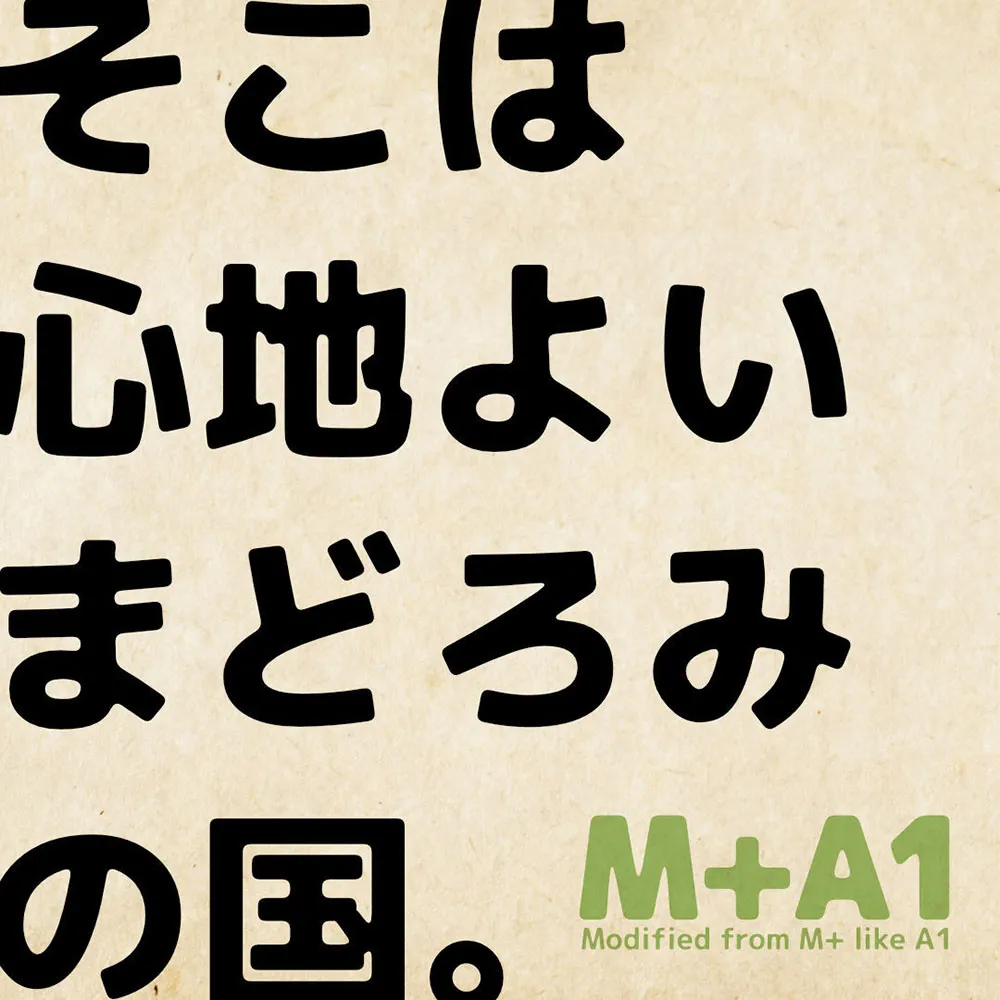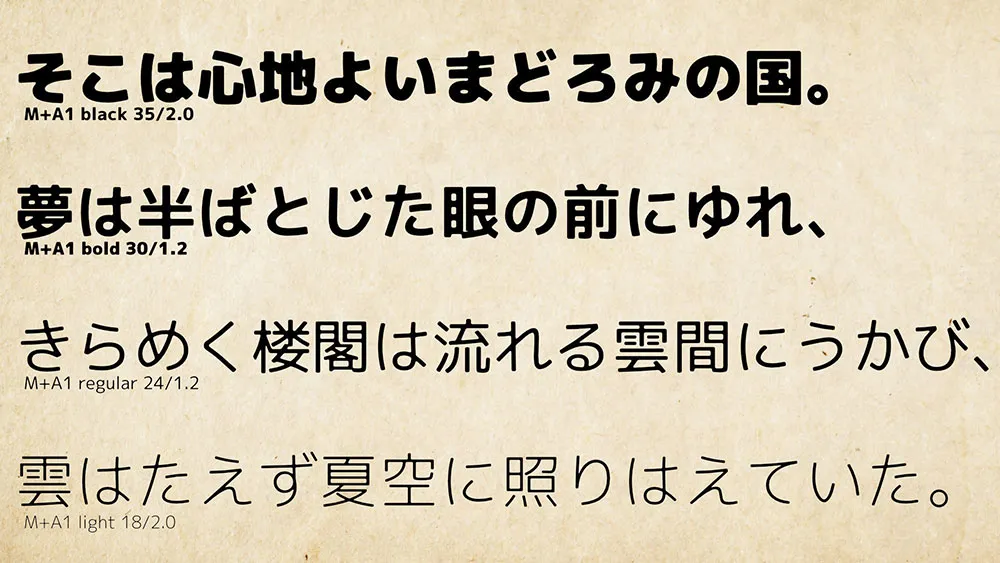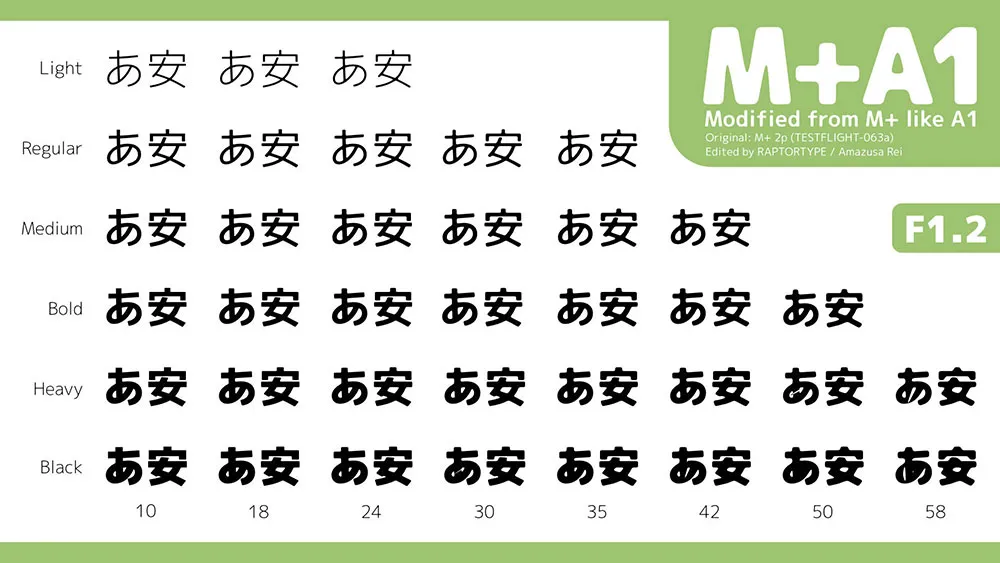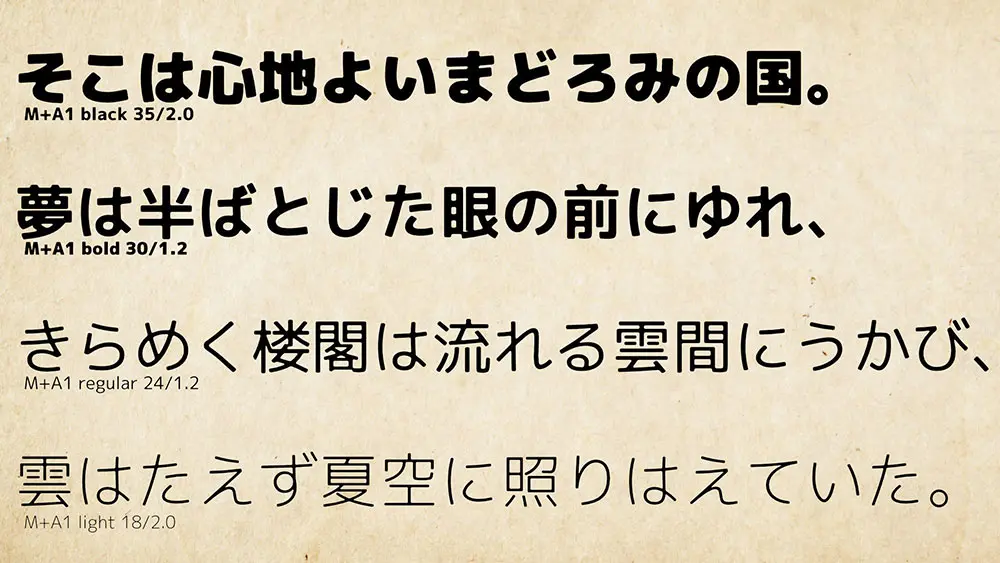
M+A1預覽
M+A1介紹
M+A1字體是對M+ FONTS進行修改,利用Python機械地進行了圓角、油墨彙集處理的字體。每個字體包含 8000 多個字符,共有74個版本。可商用,可重新發布、修改。由於機械性地編輯,一部分的文字崩塌了,使用的時候請注意。
「M+A1」フォントはM+ FONTSを改変し、Pythonにより機械的に角丸・墨溜まり処理を施した書體です。1フォント8000字以上の文字を収録、全74バージョンを用意しています。商用利用可。再頒布、改変可。※機械的に編集しているため、一部の文字が崩れています。使用の際にはご注意願います。